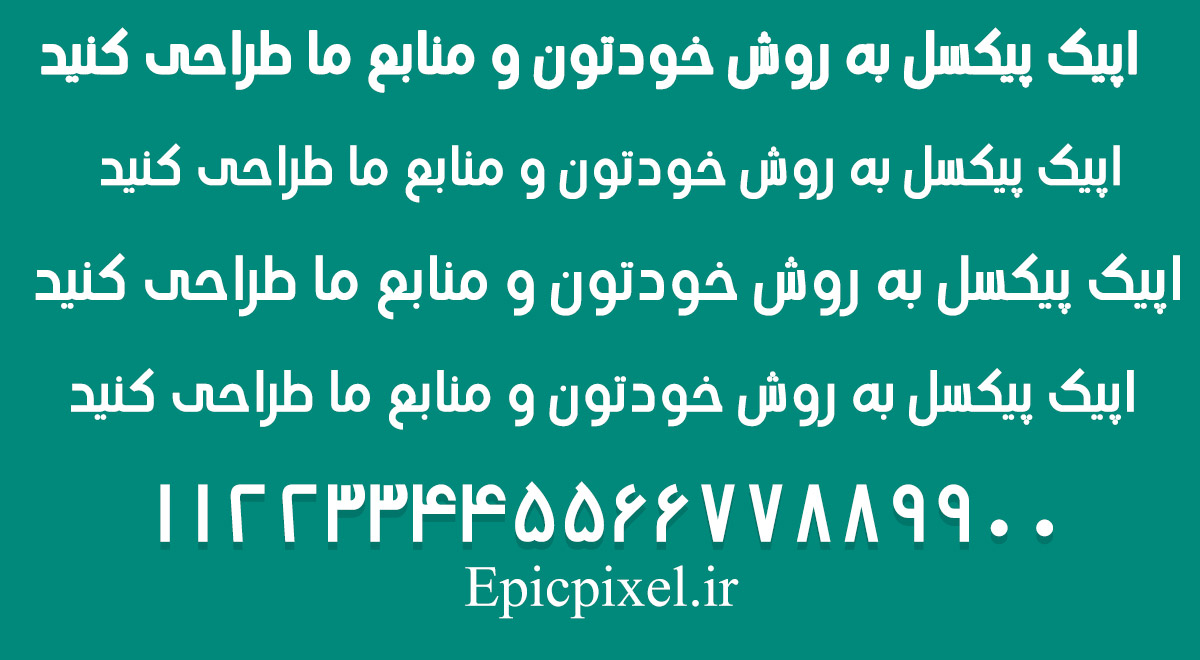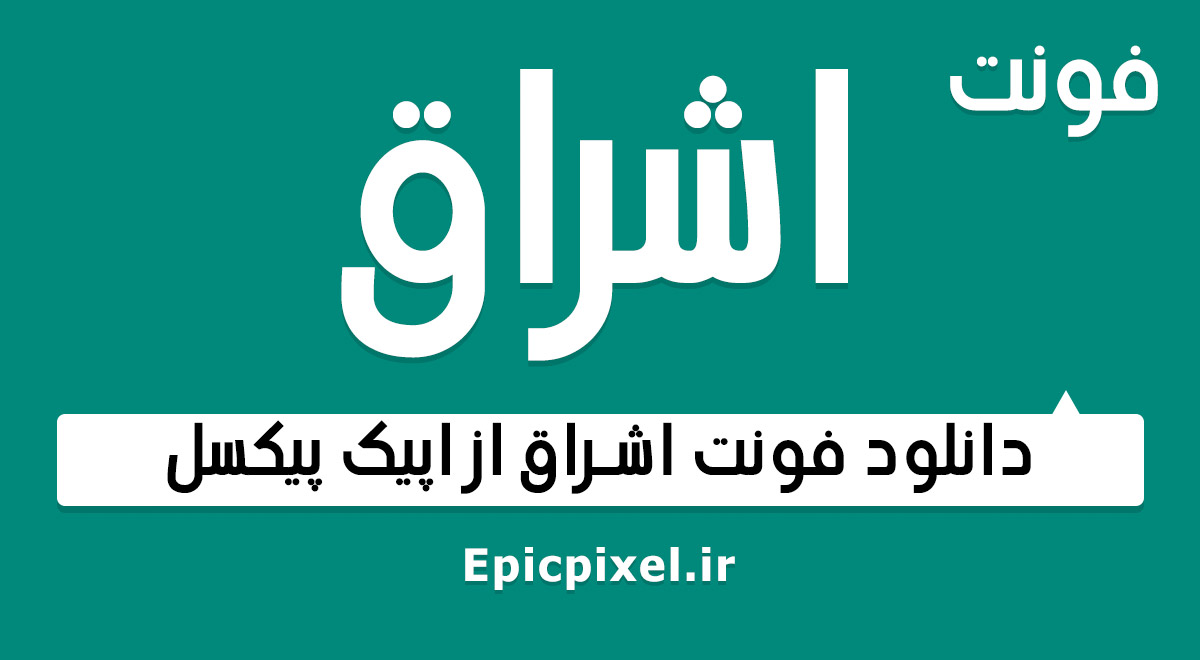
5 فونت اشراق فارسی
دانلود مجموعه کامل فونت Ishraq فارسی Font اشراق رایگان |
فونت اشراق واقعا کار بی نظیری هست
شما به کشیدگی حروف دقت کنین
یه دفرمی خاصی تو کش و قوسش وجود داره که اون رو خاص میکنه